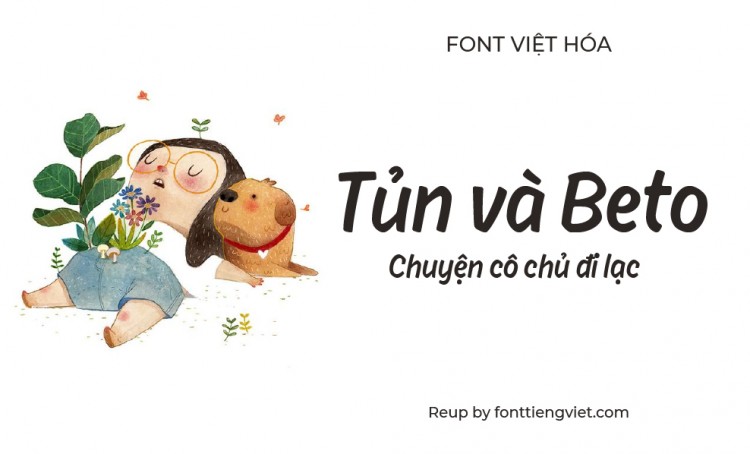
Font việt hóa Fs Ahkio (5 font)
Nếu bạn đang tìm kiếm một bộ Font Miễn Phí mang phong cách thủ công nhẹ nhàng và đầy cá tính, thì bộ Font việt hóa Fs Ahkio (5 font) chính là lựa chọn hoàn hảo nhất. Được thiết kế bởi Mika Melvas, bộ font này lấy cảm hứng từ các biển hiệu vẽ tay những năm 1930, mang lại sự hoài cổ nhưng vẫn vô cùng hiện đại. Việc sở hữu trọn bộ 5 font với các độ dày khác nhau giúp người dùng dễ dàng tùy biến cho nhiều mục đích đồ họa khác nhau tại Việt Nam.
Đặc điểm nổi bật của Font việt hóa Fs Ahkio (5 font)
Bộ font này không chỉ đơn thuần là các nét chữ mà còn là một tác phẩm nghệ thuật. Với cấu trúc đường cong mềm mại và các góc bo tròn tinh tế, bộ chữ tạo cảm giác thân thiện và dễ gần. Điều này đặc biệt phù hợp cho các bài giảng điện tử, thiết kế báo tường hoặc các tài liệu học tập trong môi trường giáo dục. Sự linh hoạt của 5 biến thể từ Light đến Black cho phép bạn sử dụng cho cả tiêu đề lẫn nội dung văn bản ngắn một cách hiệu quả.
Ứng dụng thực tế trong thiết kế
Với bộ Font việt hóa Fs Ahkio (5 font), các nhà thiết kế có thể ứng dụng vào việc làm logo, bao bì sản phẩm hoặc thiệp mời. Đặc biệt, font đã được tối ưu hóa bảng mã tiếng Việt, giúp khắc phục hoàn toàn lỗi hiển thị dấu khi gõ văn bản. Đây là yếu tố cực kỳ quan trọng đối với cộng đồng thiết kế tại Việt Nam khi muốn truyền tải thông điệp một cách trọn vẹn và thẩm mỹ nhất.